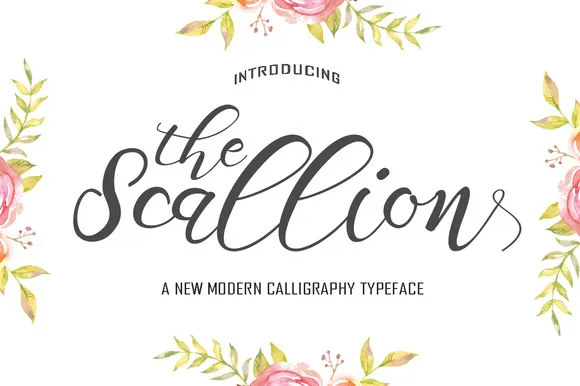
Scallion Script Font – Download Grátis
A Scallion Script Font foi criada por Polem e é parte do catálogo premium disponível na Creativemarket. Este font tem sido adorado pelos designers e amantes do desenho artístico, mas agora você pode experimentar o seu poder sem custos através desta oferta gratuita para download. Com traços finos, linhas elegantes e uma delicada harmonia de cores, a Scallion Script é perfeita para criar texturas sofisticadas em designs gráficos ou editoriais. Este font torna-se um recurso valioso para qualquer designer que deseja adicionar um toque único e rico à sua obra, sem ter que investir tempo na criação de suas próprias letras. Aproveite esta oportunidade única para experimentar a versatilidade desta fonte elegante e moderna.